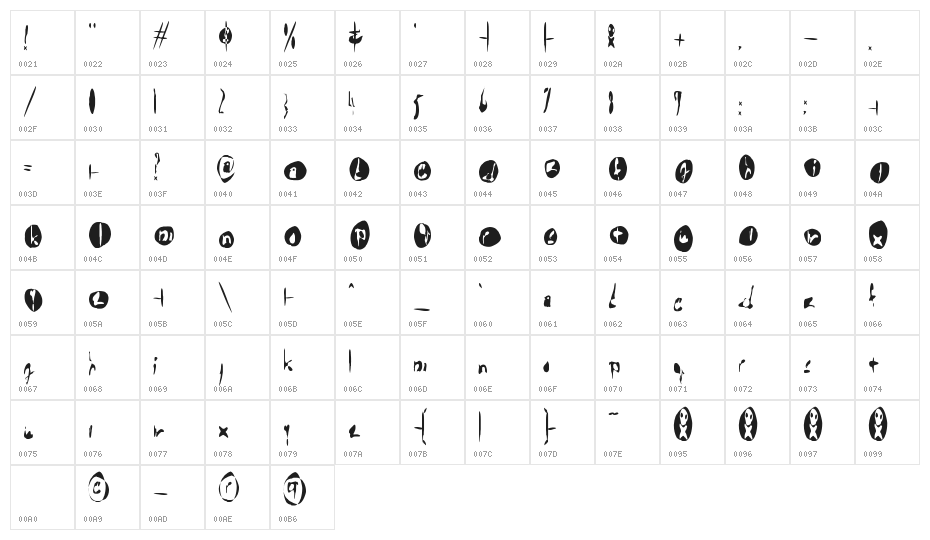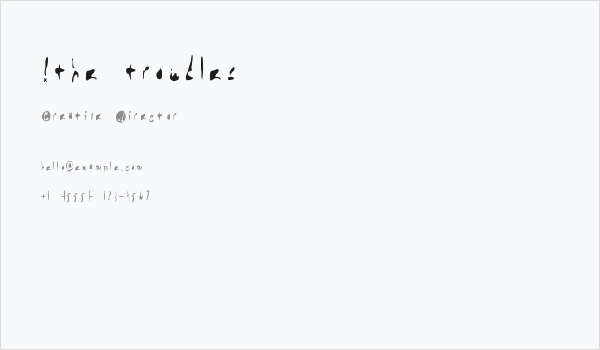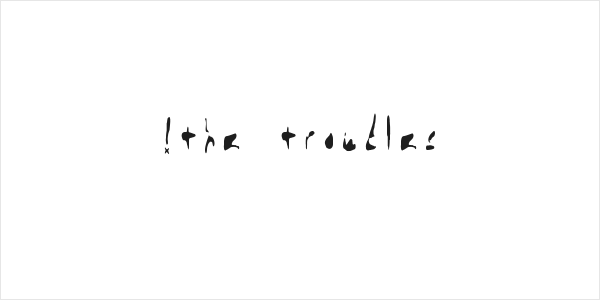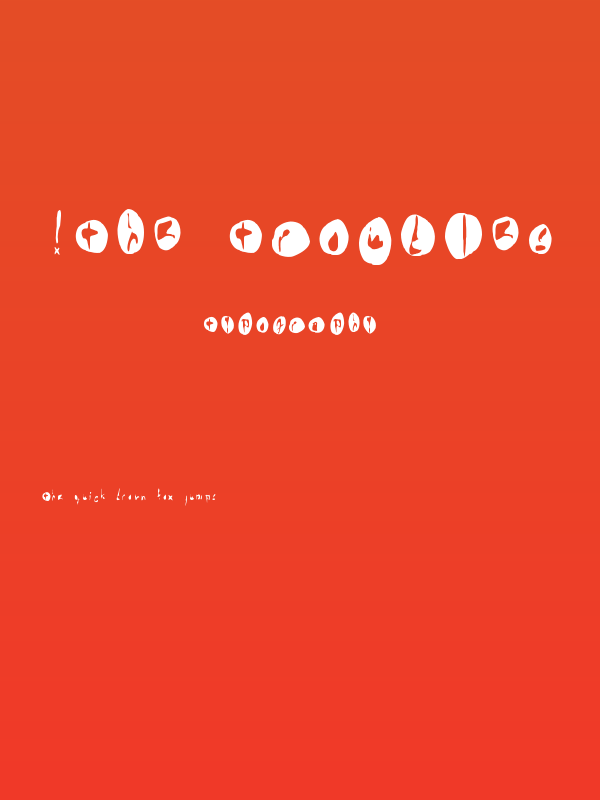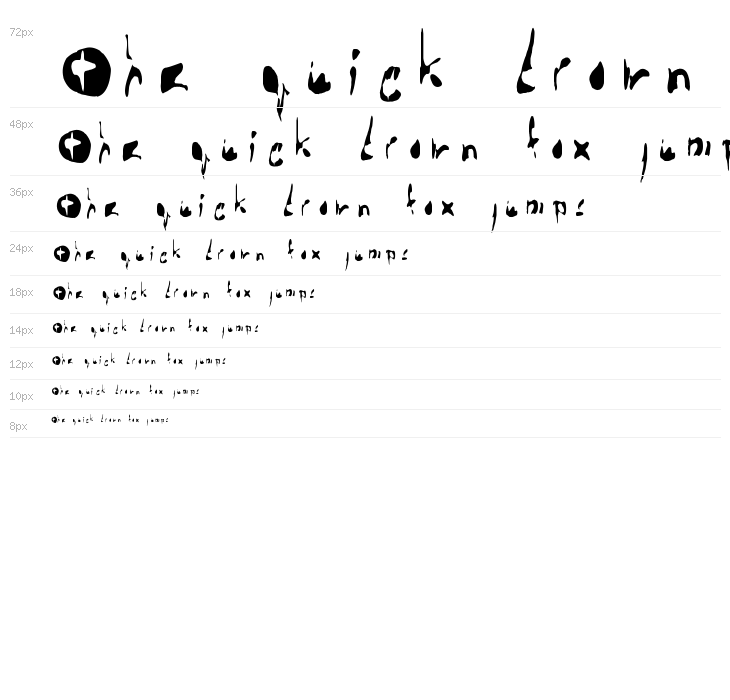
!the troubles Font
✎ Distorted Eroded
| Kategorien | Distorted Eroded |
| Gesamtstil | Avant-garde, Artistic |
| Anwendungsfall | Logos, Posters, Artistic Projects |
| Vorgeschlagene Projekte | Ideal for artistic posters, album covers, avant-garde branding, and experimental design projects. |